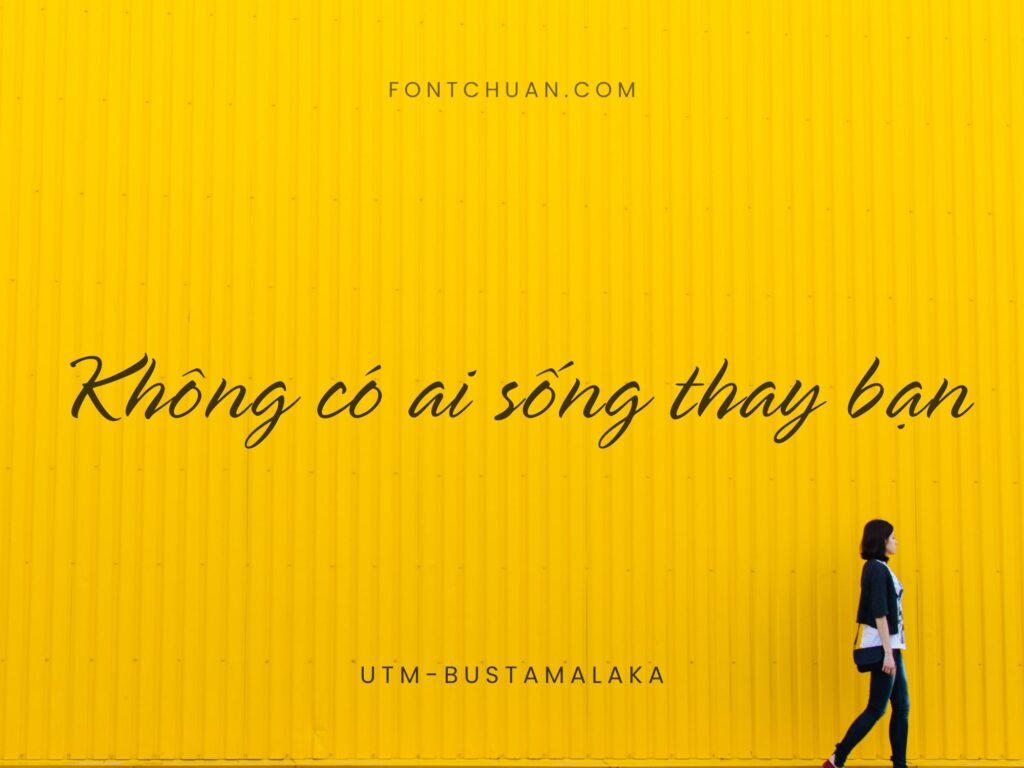
Font UTM Bustamalaka Việt Hóa
UTM Bustamalaka là phiên bản Việt hóa của font chữ Bustamalaka, một kiểu chữ decorative mang phong cách cổ điển và tinh tế, đồng thời gợi cảm hứng từ Font Vintage với các đường nét mềm mại, uyển chuyển và giàu tính nghệ thuật. Font này nổi bật với các ký tự được thiết kế tỉ mỉ, tạo cảm giác sang trọng và đậm chất hoài cổ. Phiên bản Việt hóa đã được thực hiện bởi Unicode Thiên Minh, hỗ trợ đầy đủ tiếng Việt cùng hơn 100 ngôn ngữ khác. Đây là một trong những font được cộng đồng thiết kế sưu tầm và chọn lọc nhằm đáp ứng nhu cầu đa dạng trong thiết kế.
UTM Bustamalaka có cấu trúc chữ với các nét cong mềm mại và chi tiết tinh xảo, tạo nên sự nổi bật và thu hút. Font này phù hợp cho các ứng dụng như thiết kế tiêu đề, logo, thiệp mời và các ấn phẩm in ấn yêu cầu sự trang trọng và nghệ thuật. Các ngành nghề như quảng cáo, giáo dục, công nghệ và bất động sản có thể tận dụng UTM Bustamalaka để tạo điểm nhấn độc đáo trong thiết kế.